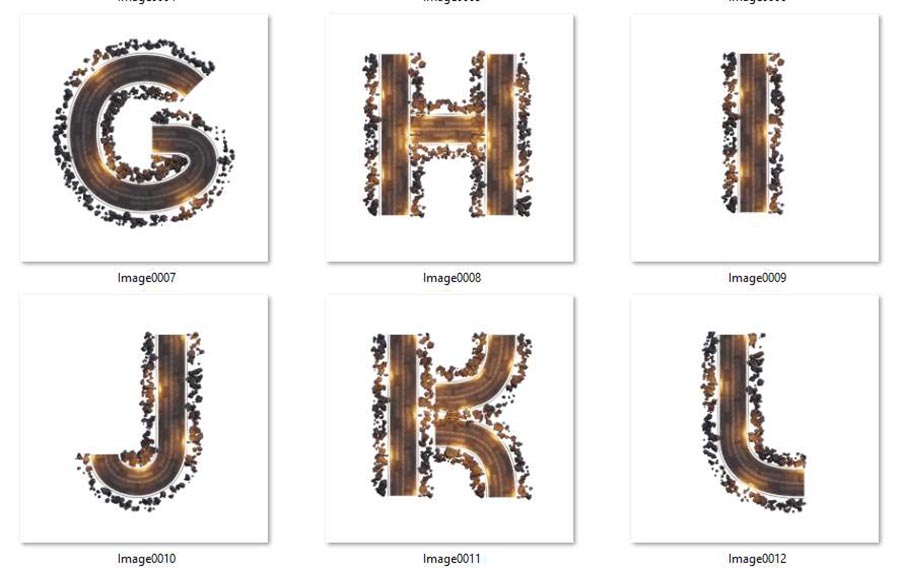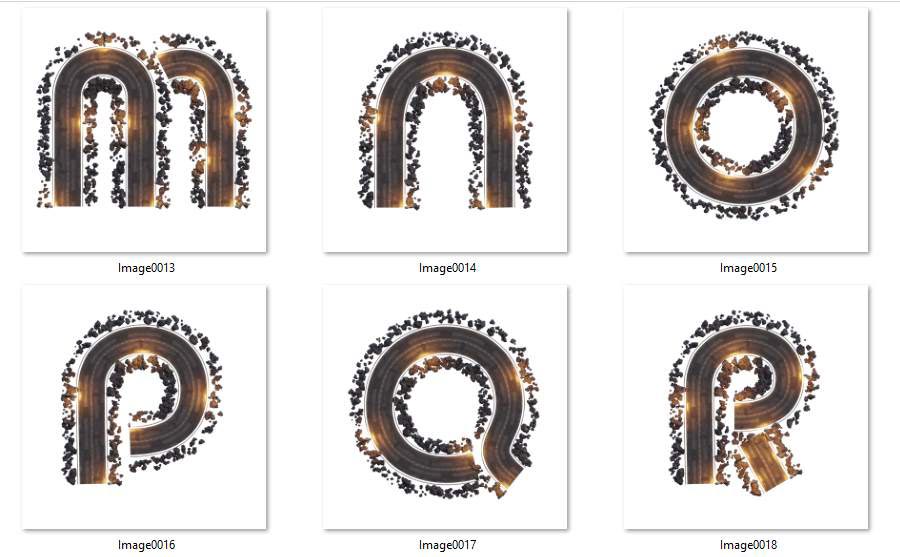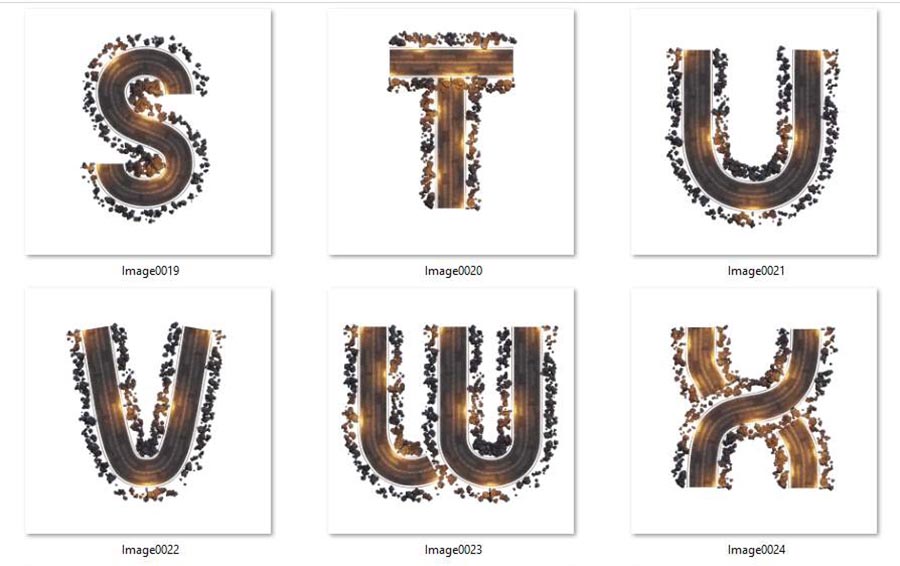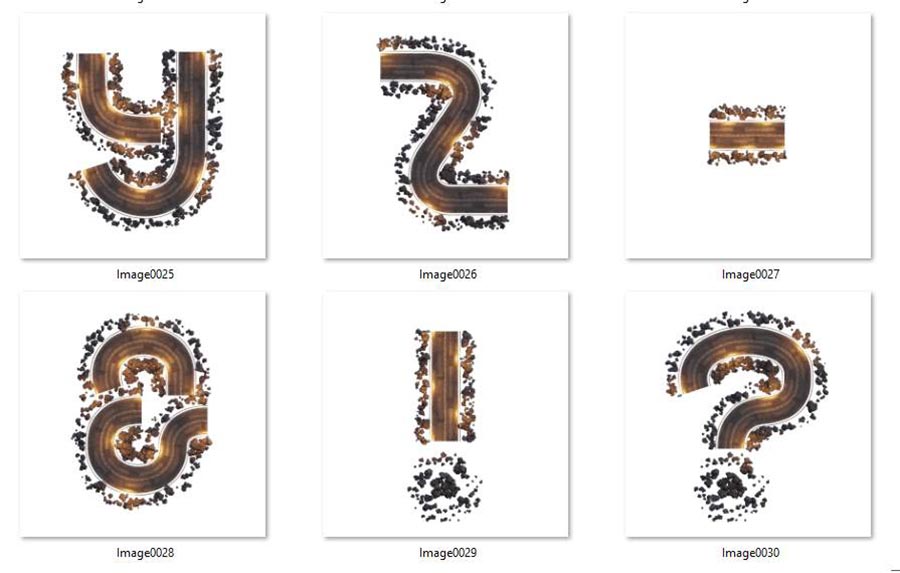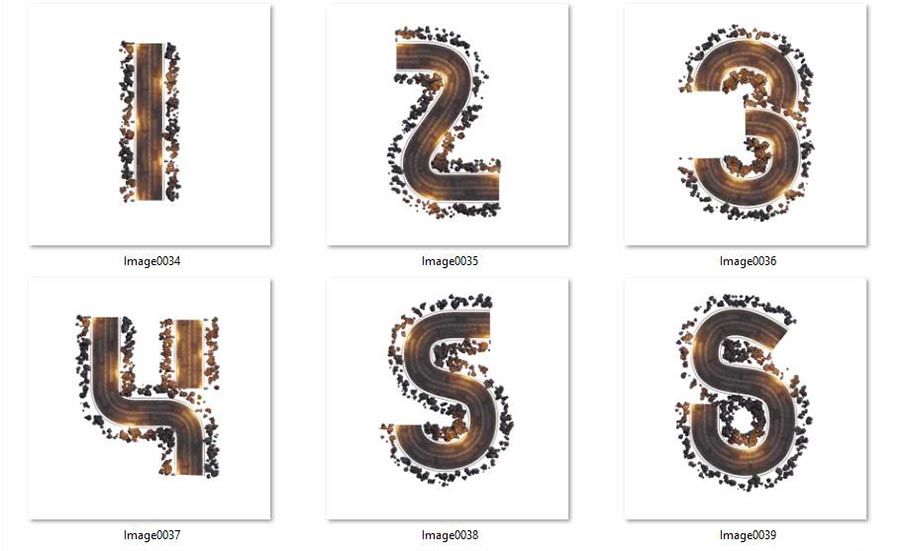
Chia Sẻ Bộ Font Chữ 3D Night Road Stock Độc Đáo Miễn Phí
Bộ chữ 3D Night Road Stock mang đến phong cách độc lạ, kết hợp giữa hiệu ứng ánh sáng đường phố ban đêm và thiết kế chữ 3D sống động. Đây là lựa chọn lý tưởng cho các dự án sáng tạo cần sự nổi bật và cá tính của bạn. Hiểu được vấn đề đó, Sadesign đã mang đến bộ font chữ 3D Night Road Stock hoàn toàn miễn phí, giúp các nhà thiết kế thỏa sức sáng tạo với phong cách riêng biệt.
1. Bộ Font Chữ 3D Night Road Stock – Nét Độc Đáo Trong Thiết Kế
3D Night Road Stock là một bộ font chữ được thiết kế với phong cách 3D đầy cuốn hút, mang đến sự mới lạ và khác biệt cho mọi sản phẩm thiết kế. Với hiệu ứng 3D sống động, font chữ này không chỉ làm nổi bật nội dung mà còn tạo thêm chiều sâu và sự chuyên nghiệp cho tác phẩm.
Không giống như những font chữ truyền thống, 3D Night Road Stock gây ấn tượng mạnh mẽ bởi các đường nét tinh tế, phá cách nhưng vẫn giữ được sự cân đối. Bộ font này đặc biệt phù hợp cho các dự án như poster, banner, thiết kế bìa sách, hoặc các sản phẩm quảng cáo đòi hỏi sự nổi bật và sáng tạo.
2. Những Điểm Nổi Bật Của Bộ Font 3D Night Road Stock
Liệt kê những điểm nổi bật của bộ font 3D night road stock mang lại gồm có:
Thiết Kế 3D Sáng Tạo
Bộ font chữ này được thiết kế với hiệu ứng 3D độc đáo, mang lại cảm giác sống động và chân thực. Các chi tiết được chăm chút tỉ mỉ, tạo nên sự khác biệt so với các font chữ thông thường.
Phù Hợp Với Nhiều Dự Án
Từ thiết kế đồ họa, quảng cáo đến các sản phẩm in ấn, 3D Night Road Stock đều có thể đáp ứng tốt. Dù bạn đang làm việc trên một dự án cá nhân hay một chiến dịch thương mại lớn, bộ font này vẫn là lựa chọn lý tưởng.
3. Ứng Dụng Của Bộ Font Chữ Trong Thiết Kế
Với sự độc đáo và sáng tạo, 3D Night Road Stock có thể được ứng dụng trong nhiều lĩnh vực khác nhau:
- Thiết Kế Poster Và Banner: Font chữ 3D giúp tạo điểm nhấn mạnh mẽ, thu hút sự chú ý từ người xem.
- Thiết Kế Logo: Các thương hiệu muốn tạo dựng hình ảnh hiện đại và khác biệt có thể sử dụng bộ font này để thiết kế logo.
- Thiết Kế Bìa Sách Hoặc Tạp Chí: Hiệu ứng 3D mang lại cảm giác chuyên nghiệp và đẳng cấp cho các sản phẩm in ấn.
- Quảng Cáo Trực Tuyến: Với tính năng nổi bật, font chữ này dễ dàng gây ấn tượng trong các chiến dịch quảng cáo trên mạng xã hội hoặc website.